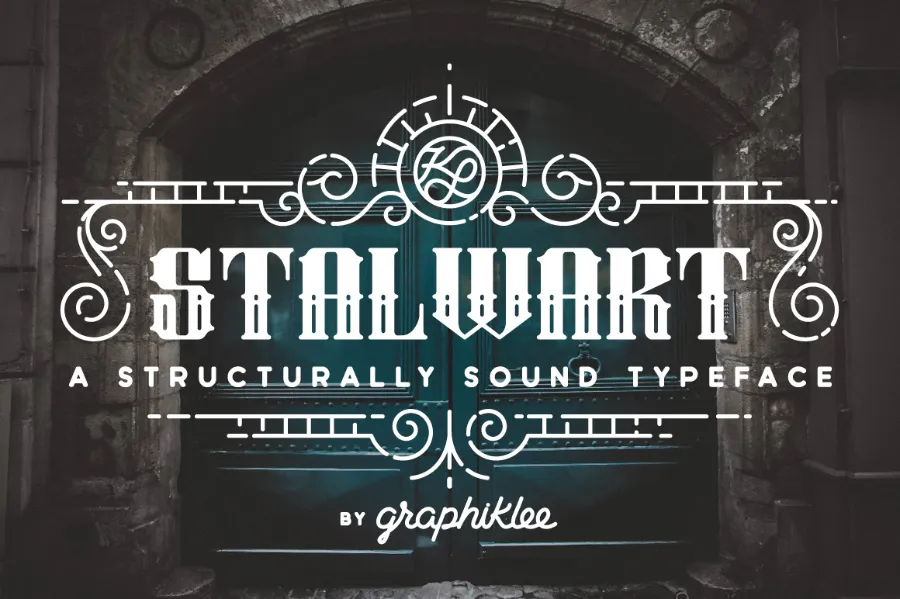
Stalwart Typeface – Download Grátis
Introduzimos a nova tipografia exibição Stalwart Typeface criada pela graphiklee. Esta tipografia foi inspirada por elementos encontrados na arquitetura, carpintaria e letra de tatuagem. Consiste em larguras horizontais e verticais uniformes para uma base sólida, perfeita para logotipos, headlines e ilustrações. Pela sua consistência, Stalwart é um bom par com designs monoline. Independentemente do estilo vintage ou moderno que buscas, a graphiklee criou esta fonte de tal forma que o seu trabalho ganha um aspeto que permanecerá ao longo dos tempos. Esta tipografia é perfeita para quem quer dar um toque único e duradouro aos seus projetos visuais. Stalwart Typeface é uma excelente adição à tua coleção de fontes, especialmente se procura algo forte e confiável.